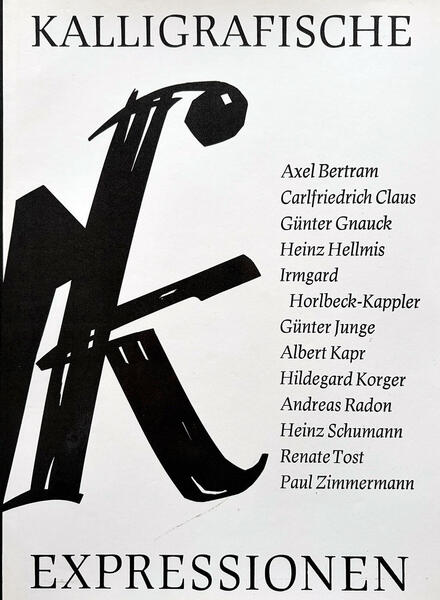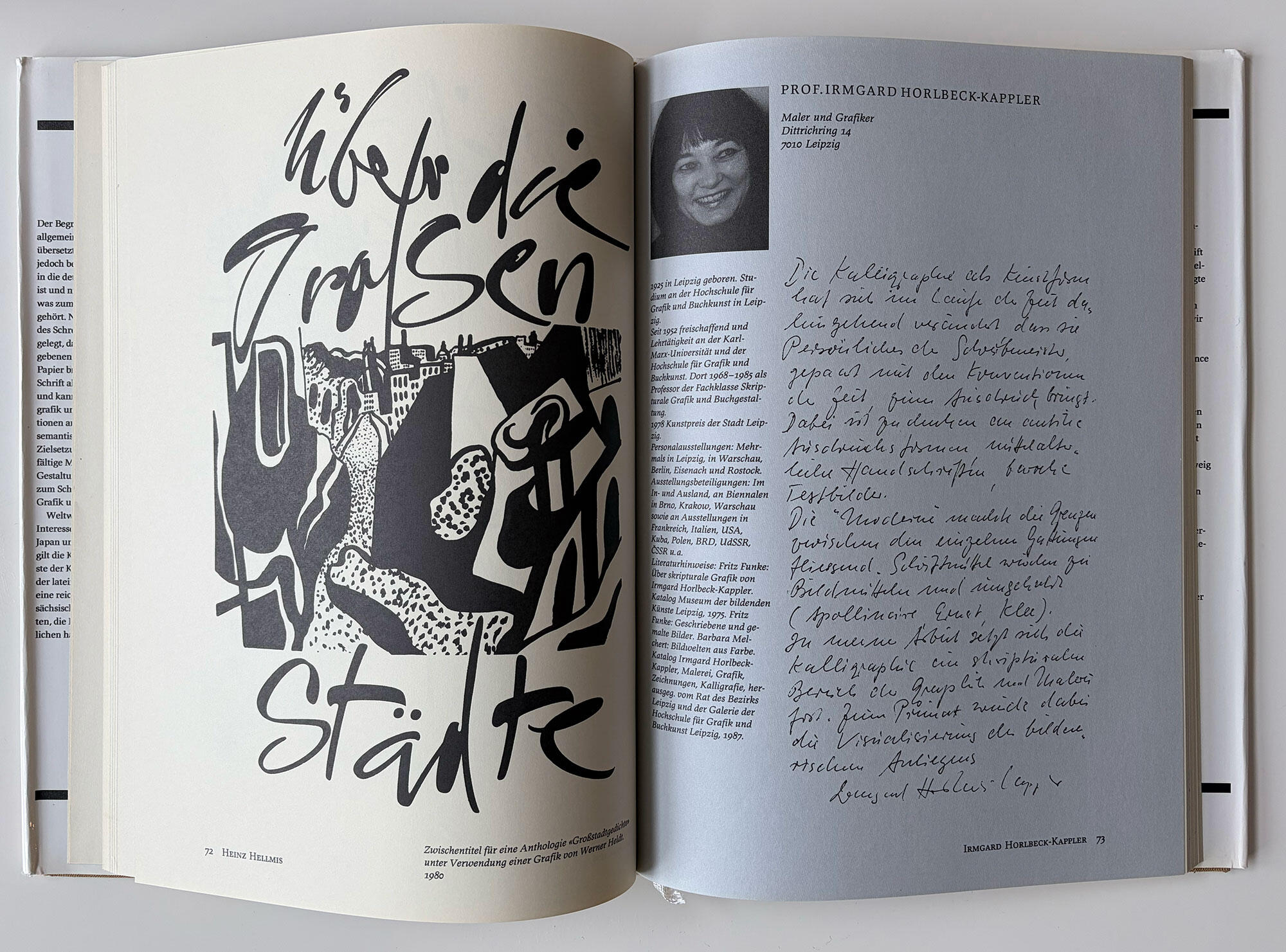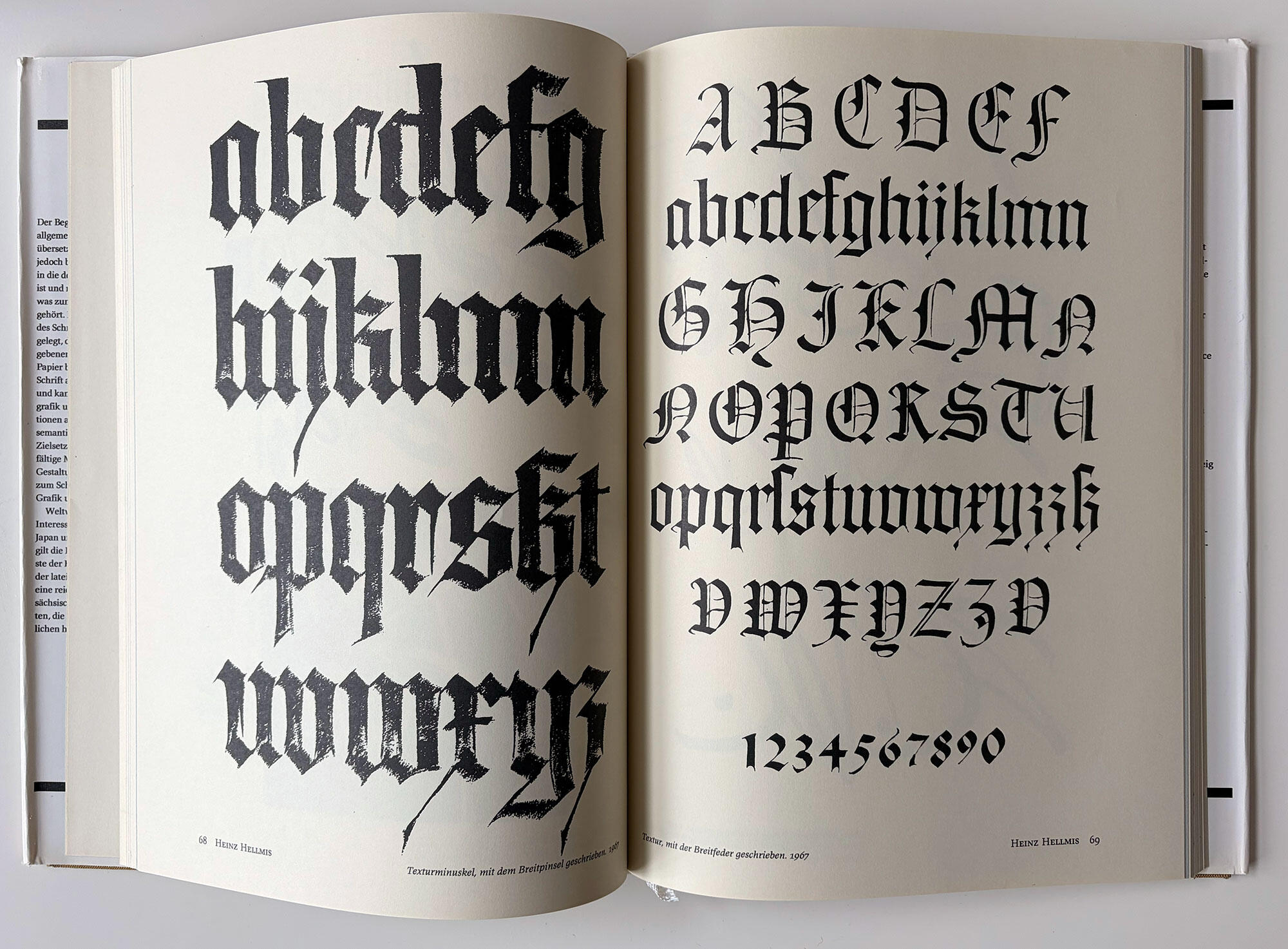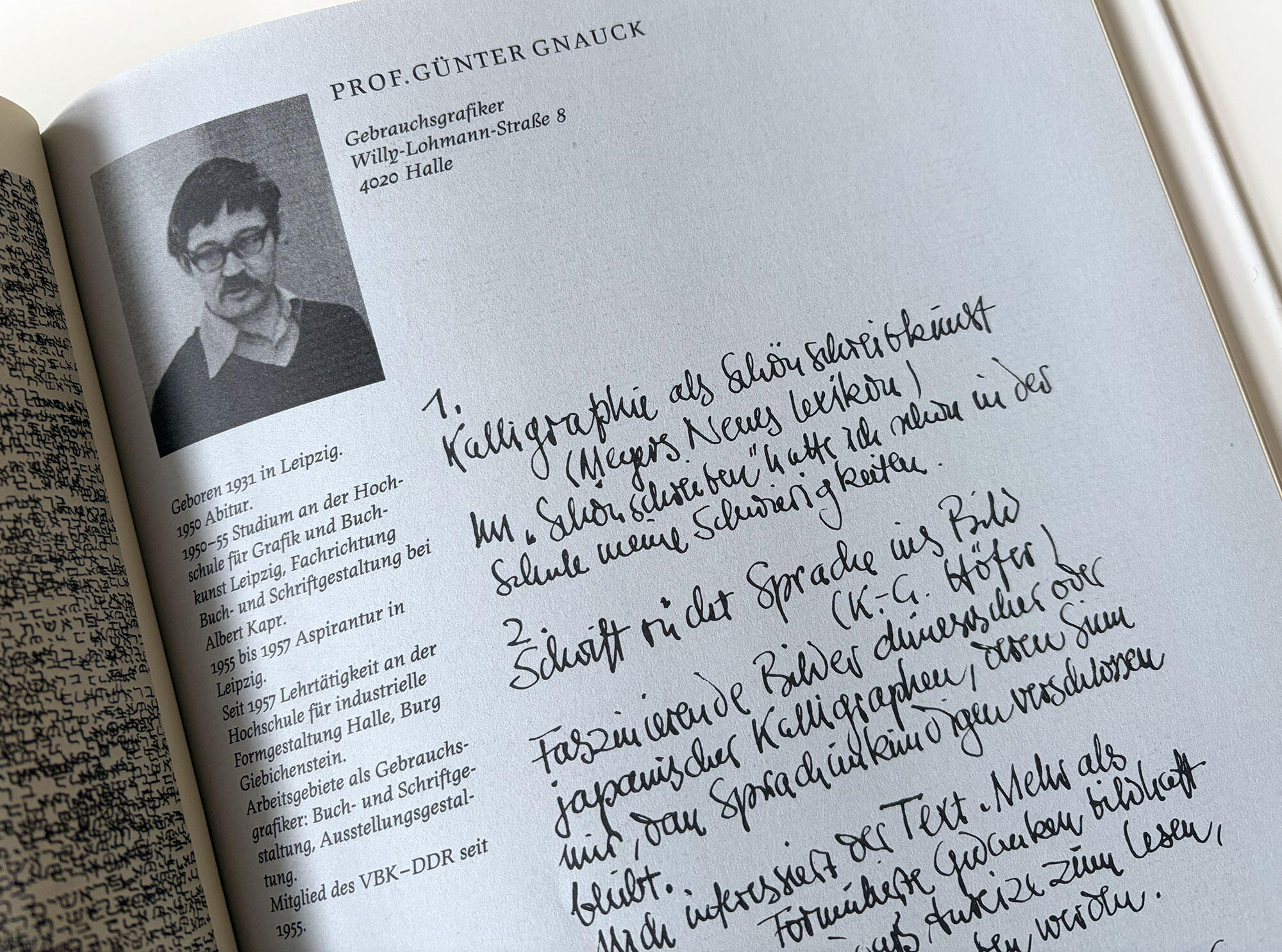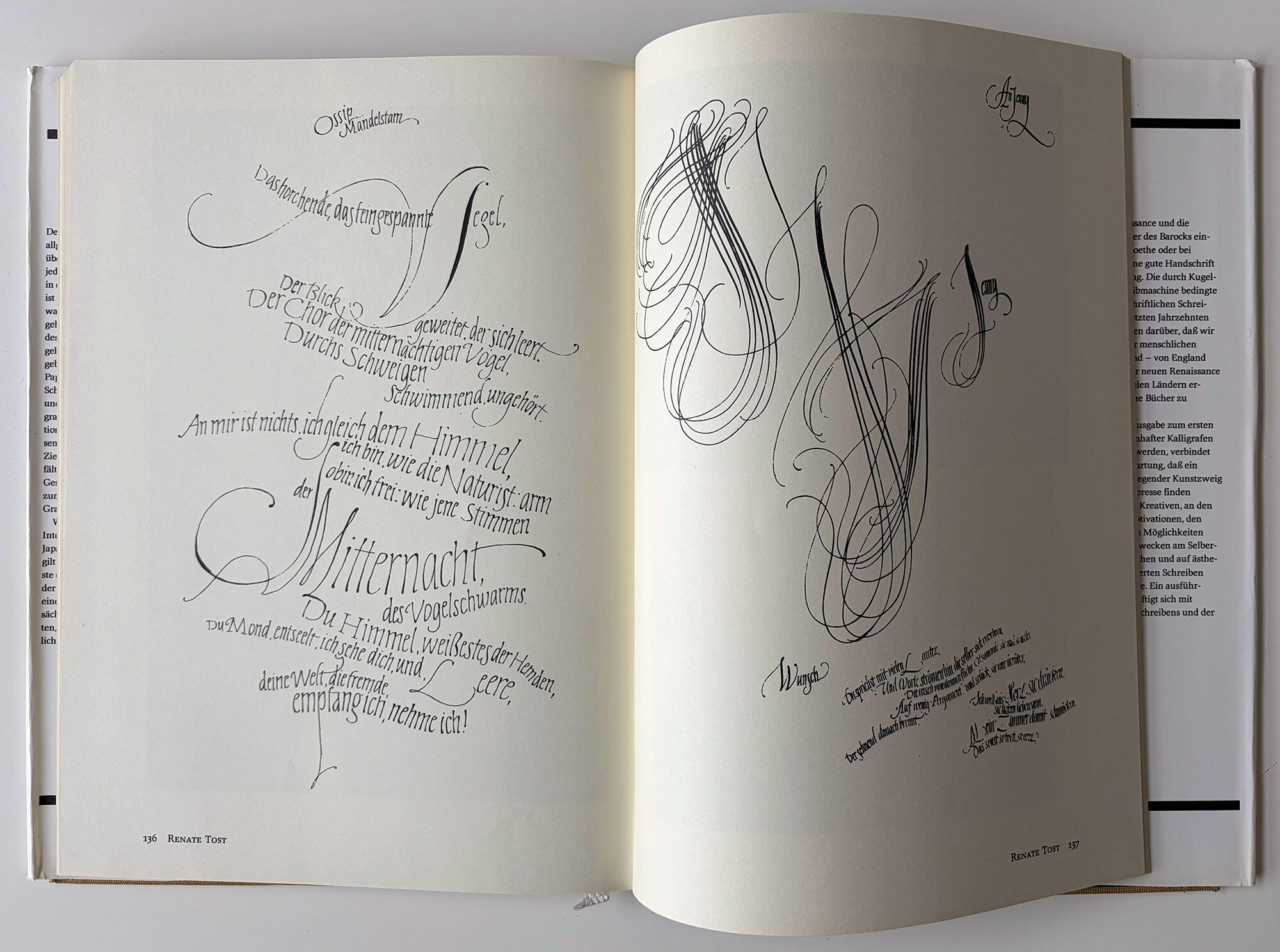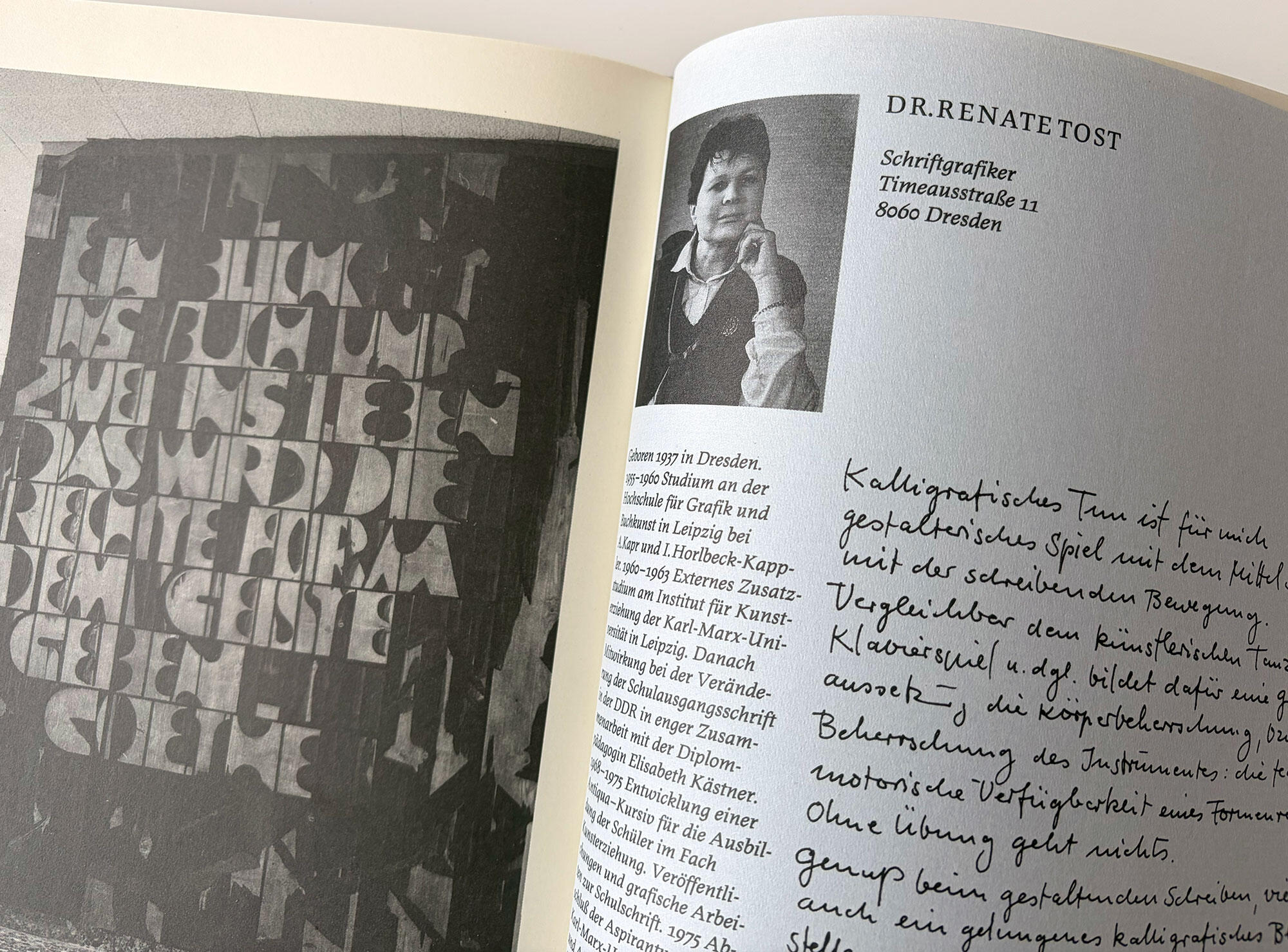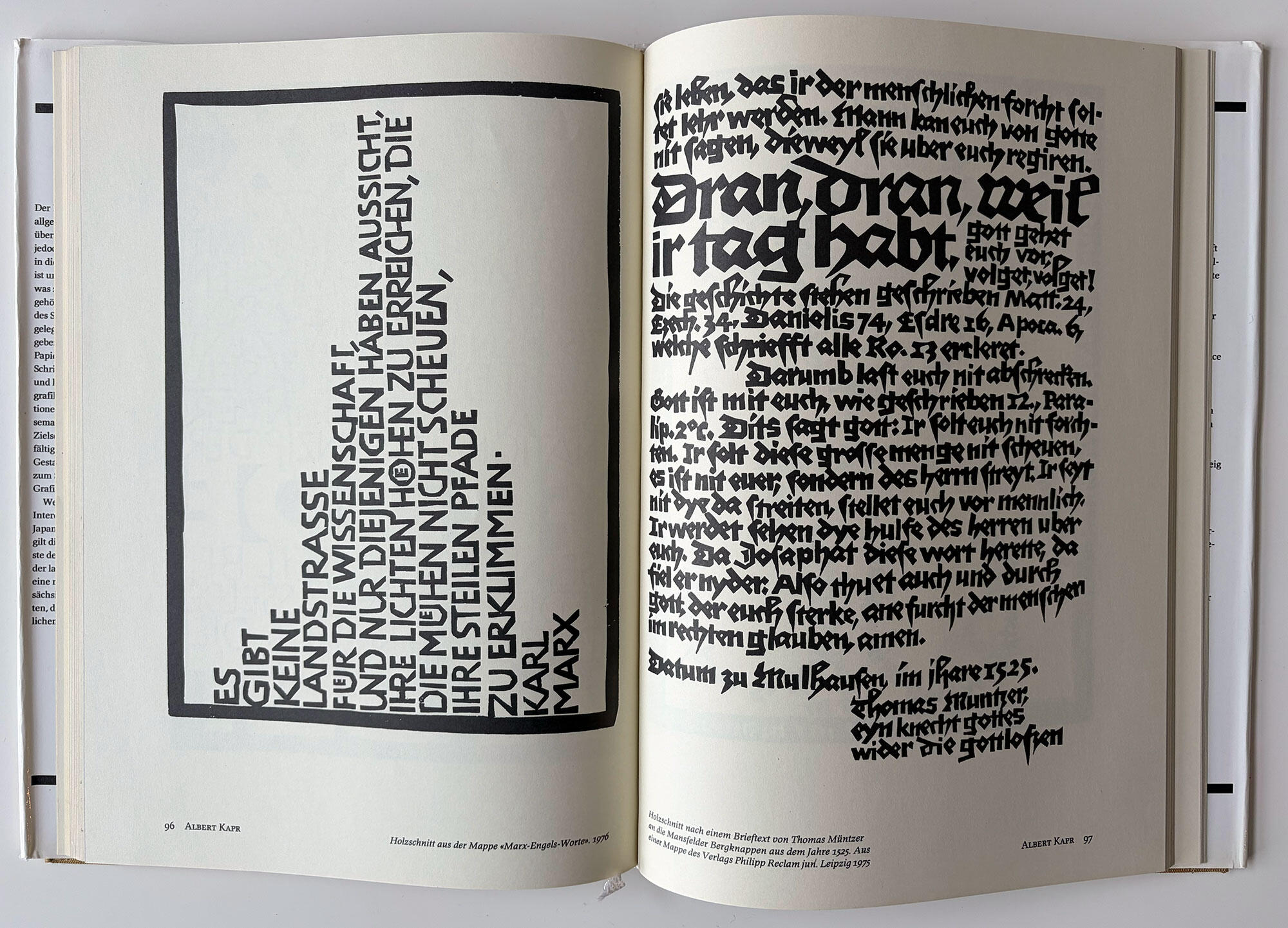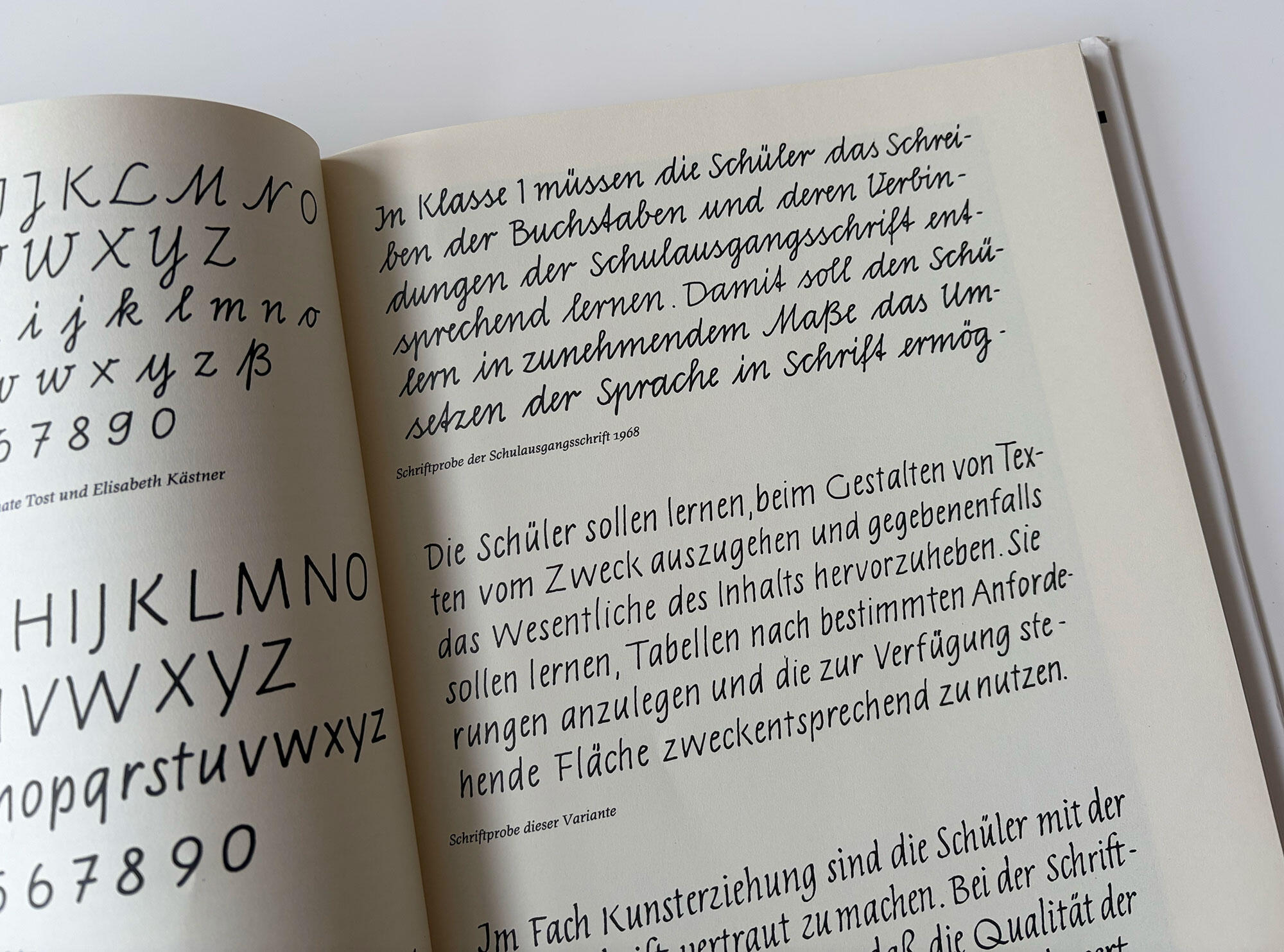
Das Buch »Kalligrafische Expressionen« dokumentiert kalligrafische Arbeiten von 12 ostdeutschen Schriftkünstlern und erschien 1988 im Fachbuchverlag Leipzig. Die Künstler sind Axel Betram, Carlfriedrich Claus, Günter Gnauck, Heinz Hellmis, Irmgard Horlbeck-Kappler, Günther Junge, Albert Kapr, Hildegard Korger, Andreas Radon, Heinz Schumann, Renate Tost und Paul Zimmermann.
Im Klappentext heißt es: »Wenn mit dieser Ausgabe zum ersten Mal ein Dutzend namhafter Kalligrafen der DDR vorgestellt werden, verbindet sich dies mit der Erwartung, daß ein bislang im Schatten liegender Kunstzweig mehr öffentliches Interesse finden möge. Die Freude am Kreativen, an den unterschiedlichen Motivationen, den vielfältigen grafischen Möglichkeiten könnte auch die Lust wecken am Selbermachen, am spielerischen und auf ästhetische Qualität orientierten Schreiben für sich und für andere.«
Ein Vorwort des Herausgebers Albert Kapr widmet sich zunächst verschiedenen Aspekten des Schreibens und der Kalligrafie. Dann folgen für jeden einzelnen Künstler mehrere Seiten. Abgebildet wird jeweils eine Biografie, eine handschriftliche, persönliche Einlassung zur Kalligrafie sowie zahlreiche schriftgestalterische Arbeitsproben.
Untertitel: Über die Kalligrafie in der Deutschen Demokratischen Republik
Autor(en): Albert Kapr (Herausgeber/Einleitung)